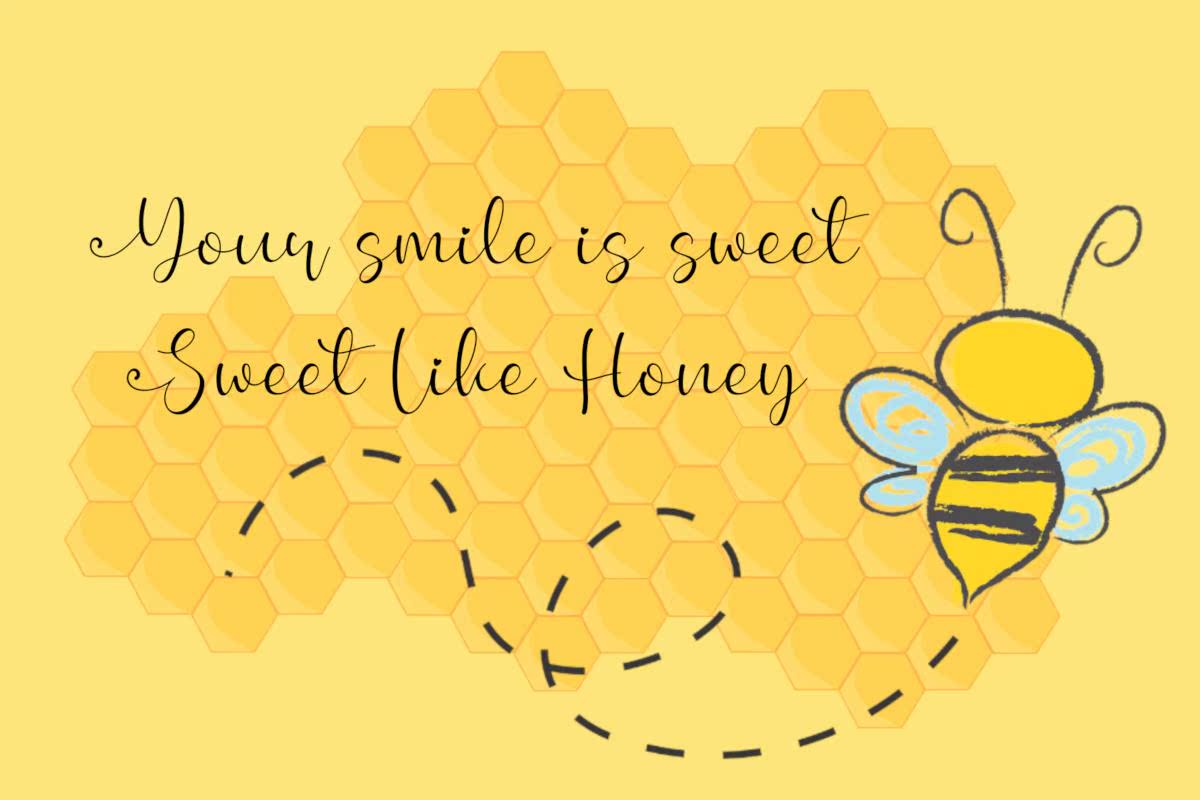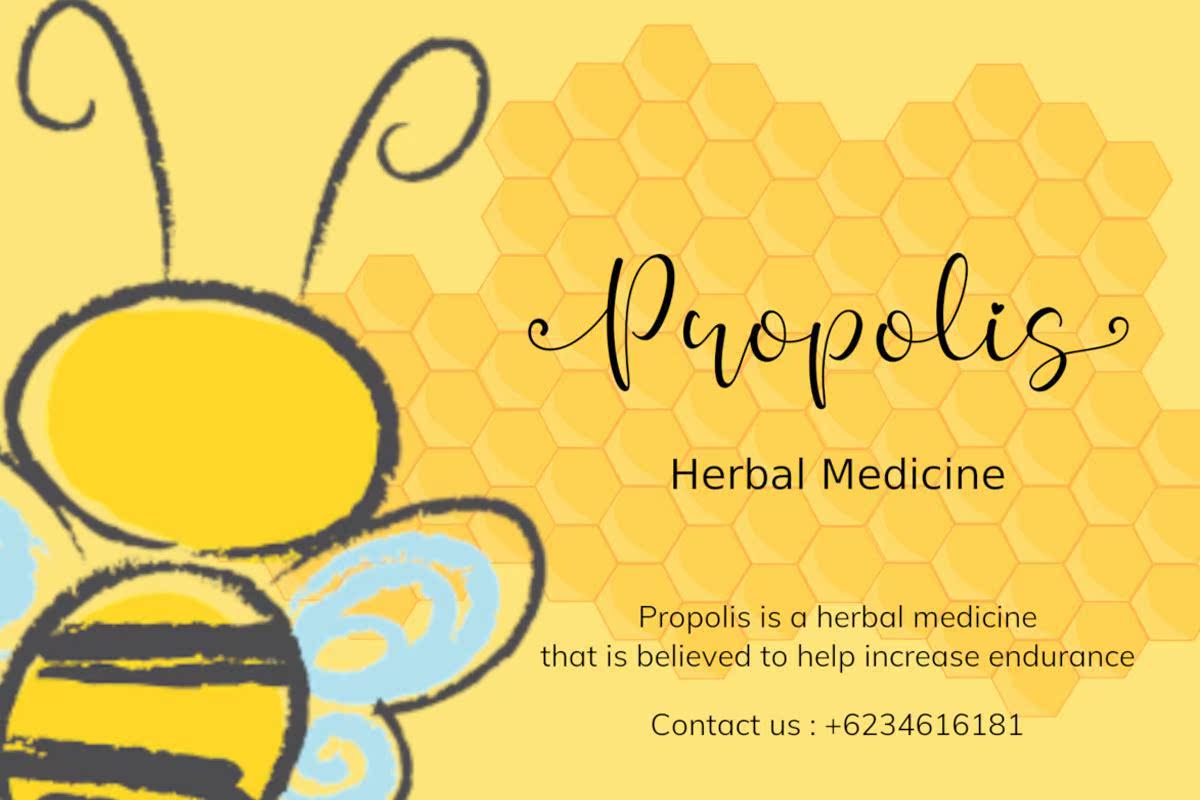
Free Demobutthey Honey Handletting Font是AVTYPE的一款漂亮的全手写字体。它自然具有让您的作品看起来更专业的特征。它将赋予您独特的触感,让您的设计看起来更漂亮。因此,这款FreeFont适用于婚礼、贺卡、T恤、logo或任何您想到的设计。因此,现在下载并拥有功能创建,但是你只有个人许可证。因此,如果你有更多的功能,如连接性、商业用途和其他功能,请购买PremiumVersion。